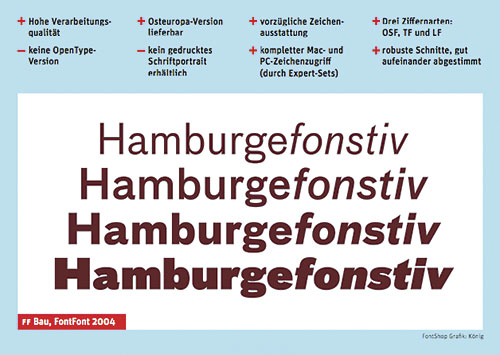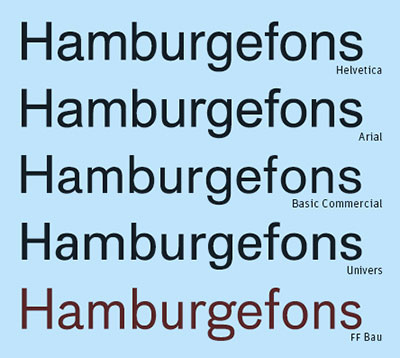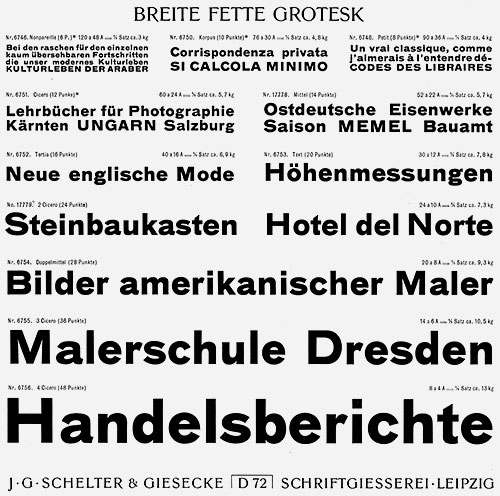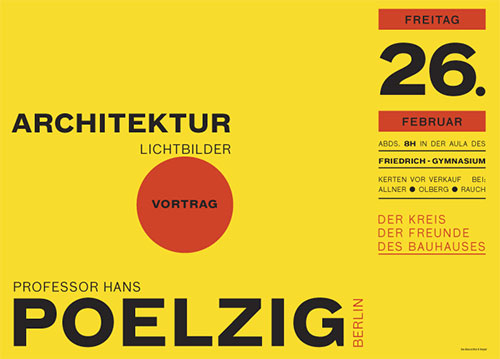
Bau: Mutter Sans und ihre KinderDie Leipziger Schriftgießerei Schelter & Giesecke
veröffentlichte um 1880 eine bemerkenswerte, linear konstruierte
Grotesk-Schrift. Sie diente Max Miedinger Jahre später als Vorlage
zur Helvetica. Der US-Schriftentwerfer Christian Schwartz hat die
Scheltersche Grotesk werkgetreu digitalisiert und als Bau
![]() Das Schriftentwerfen ist keine Kunst, sondern Handwerk. Schriften sind
Rohmaterial, das dazu dient, geschriebenen Text zum Leben zu erwecken. Die
gehobene Form dieser Profession nennen wir Typografie. Erstklassige
Typografinnen und Typografen behandeln Schriften wie eine Kapitalanlage,
deren Wertsteigerung sie mit ihrer Gestaltungsarbeit selbst bestimmen.
Die junge Schriftfamilie FF Bau aus der FontFont-Bibliothek (2005-Katalog-Nachtrag als PDF) ist ein solcher Schatz, der eine Lücke im weltweiten Schriftangebot schließt. Obwohl nahezu alle Erfolgsschriften der Bleisatzära in den Fundus des Computersatzes Eingang gefunden haben, lag die »Mutter aller Sans-Serifs« bislang in keinem digitalen Format vor. Die Rede ist von Schelter Grotesk, der Vorlage für FF Bau. Die Leipziger Schriftgießerei Schelter & Giesecke veröffentlichte sie um 1880: eine linear konstruierte, wegweisende Serifenlose, die sofort für Aufsehen sorgte und ein Longseller wurde. Jahre später dient sie Max Miedinger als Vorlage für Helvetica, die bei ihrer Premiere unter dem Namen Neue Haas Grotesk auf den Markt kam. ![]() Die fette Scheltersche Grotesk, Reproduktion eines Schriftmusters (um 1900), das als Vorlage für die Bau diente Schelter Grotesk sieht aus wie eine gefällige Spielart der Akzidenz Grotesk, mit Antiqua-(Doppeldecker)-g, kleiner Mittellänge und schmaleren Zeichen. Ein wahres Arbeitstier, ohne Wenn und Aber einsetzbar für den Mengensatz, der jahrhundertelang von Serifenschriften dominiert wurde. Im Bauhaus kam sie laufend zum Einsatz, weil deren Setzerei noch üppig mit Schelter-Blei bestückt war. Auch der große Typograf Jan Tschichold verwendet sie gerne. 1999 fiel FontShop-Gründer Erik Spiekermann eine Original-Satzprobe der Schelter Grotesk in die Hände, die er seinem »Hof-Digitalisierer« Christian Schwartz weitergab, um zu prüfen, ob sich aus den Vorlagen brauchbare Computerschriften generieren ließen. Wer wäre besser geeignet, eine Bleisatzschrift zu neuem Leben zu erwecken als Schwartz? Er lernte fast zwei Jahre bei David Berlow, dem Gründer des Bostoner Font Bureau, Inc. bekannt für exzellente Schrift-Reeditionen und großes handwerkliches Können. Christian Schwartz nahm sich in den folgenden Jahren immer wieder der Schelter Grotesk an. Er zeichnete jeden der gerade stehenden Schnitte, also jede Strichstärke, einzeln neu, um die Eigenheiten des Originals zu verstehen und zu erhalten. Heute werden üblicherweise Schriften aus zwei Extremen, zum Beispiel Light und Black, interpoliert. Diese Rationalisierung ist verständlich und nicht zu verteufeln, denn mit einiger Erfahrung ergeben sich konsistente, brauchbare Resultate. ![]() Plakat des Designers und Bauhaus-Lehrers Herbert Bayer, nachgesetzt von Christian Schwarz mit seiner FF Bau Im Falle der Schelter Grotesk war das oberste Gebot, ihren »Spirit« und ihre Wärme ins digitale Zeitalter hinüber zu retten. Es gab damals keinen extrafetten Schnitt, was Schwartz zum Anlass nahm, eine Super ganz neu zu entwerfen. Warum Super? Darauf gibt es zwei klare Antworten: Erstens macht der extrafette Schnitt die Familie erst wirklich Headline-tauglich (wir kennen die Vorliebe der US-Magazingestalter für eng gesetzte, superfette Überschriften) und zweitens brachte diese Zugabe dem Entwerfer genau jenen Interpretationsraum, der für das Werk wie auch die persönliche Entwicklung lebenswichtig ist. ![]() Das Ergebnis des FontShop-Schrift-Test der FF Bau, (entnommen dem Magazin fonts 1) So ist der Super-Schnitt der eigentliche Glanzpunkt der FF Bau, die zunächst »FF Haus« heißen sollte, aber der Name war bereits vergeben. Die bulligen, kompakten Lettern mit ihren fast verschwindenden Innenräumen heben die Familie klar ab von allen bisherigen Derivaten. Anfang 2004 kam die FF Bau bei FSI FontShop International heraus: 4 Strichstärken mit Mediävalziffern als Standard, alternativ je 4 Schnitte mit Versal- und Tabellenziffern; Expert-Schnitte mit Sonderzeichen rundeten das 22 Fonts umfassende Paket ab. Leider fehlte eine Kursive, ohne die eine Textschrift nahezu unverkäuflich ist. Das musste auch Erik Spiekermann jüngst mit seiner FF Unit erfahren, die bei den Kunden erst richtig Anerkennung fand, als die Italic lieferbar war, fast ein Jahr nach der Erstvorstellung. Zur Freude der schnell wachsenden Bau-Interessengemeinde ließ die Italic nicht lange auf sich warten. Noch vor Ende 2004 lag sie in den Regalen, ebenso gut ausgebaut und sorgfältig digitalisiert wie die geraden Schnitte. ![]() Die Verwandten der FF Bau im Vergleich mit der »Mutter« Ihre Geschichte ist ähnlich abenteuerlich wie die von FF Bau Roman. Das US-Magazin Men’s Fitness verordnete sich Anfang 2004 ein Redesign, und da lag es nahe, die neue, muskulöse FF Bau Super als Headline-Schrift einzusetzen. Die leichteren Schnitte sollten für die Lesetexte zum Einsatz kommen. Aber ohne Kursive zum Auszeichnen? Ein Ausschlusskriterium. Doch Neal Boulton, der Design-Berater der Life-Style-Zeitschrift, griff selbst zum Stift und legte den Grundstein für vier kursive Schnitte, die bei Font Bureau unter großem Zeitdruck digitalisiert wurden. »Ein guter Anfang, doch nur wenig davon ist in der endgültigen Fassung von FF Bau Italic enthalten« betont Christian Schwartz heute: »Vieles musste in eine andere Richtung gebracht werden.« Wenige Wochen später war sie fertig, FF Bau wurde komplett. Das Nachliefern von Schriftergänzungen gehört zu jener Art Verführungskunst, die FontFont-Herausgeber FSI perfekt beherrscht. Sicher auch ein Grund dafür, dass die Schriften der FontFont-Bibliothek den Wünschen ihrer Benutzer stets auf den Fersen folgen. ![]() Schriftentwerfer Christian Schwartz (New York) gehört zu den großen Könnern seiner Gilde Herausgegeben: Mo - September 12, 2005 at 02:17 nachm. | |